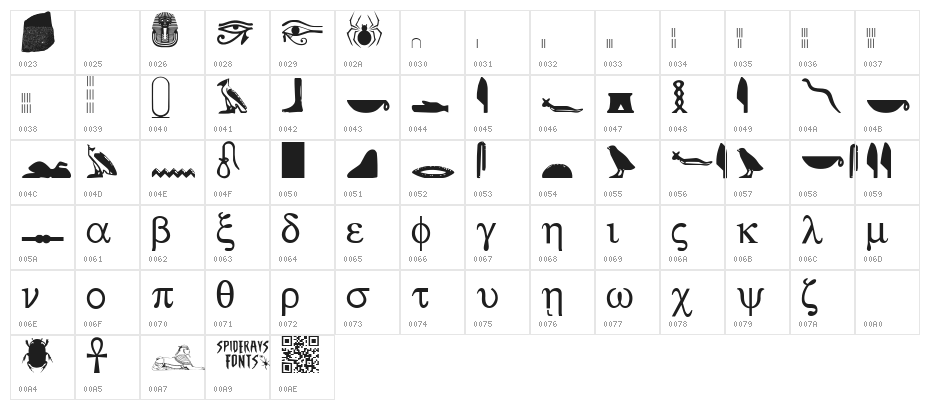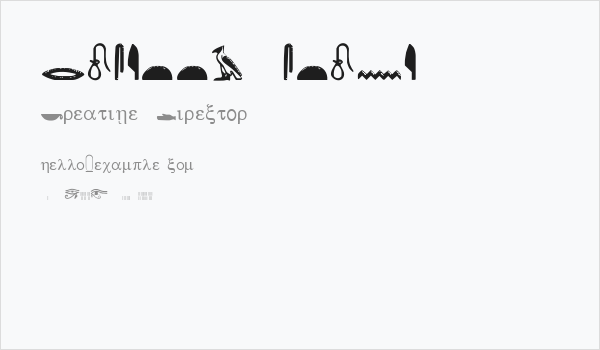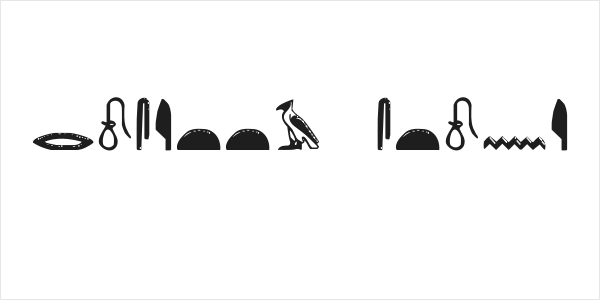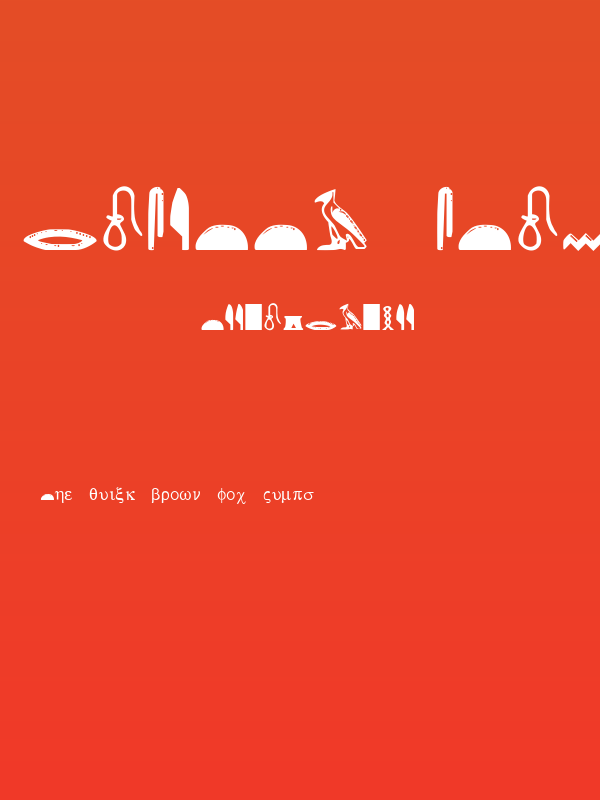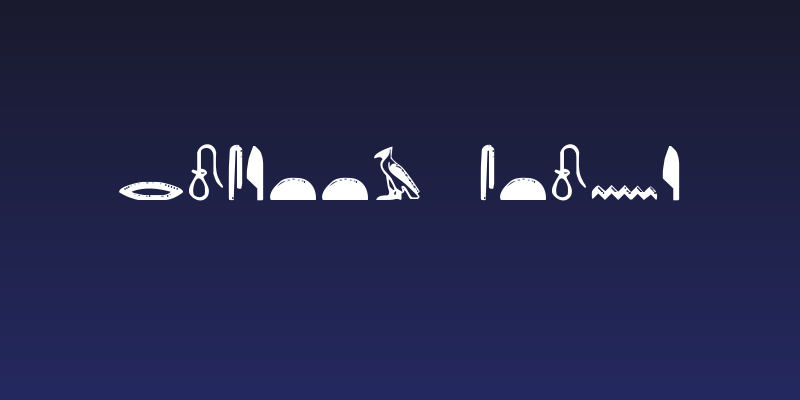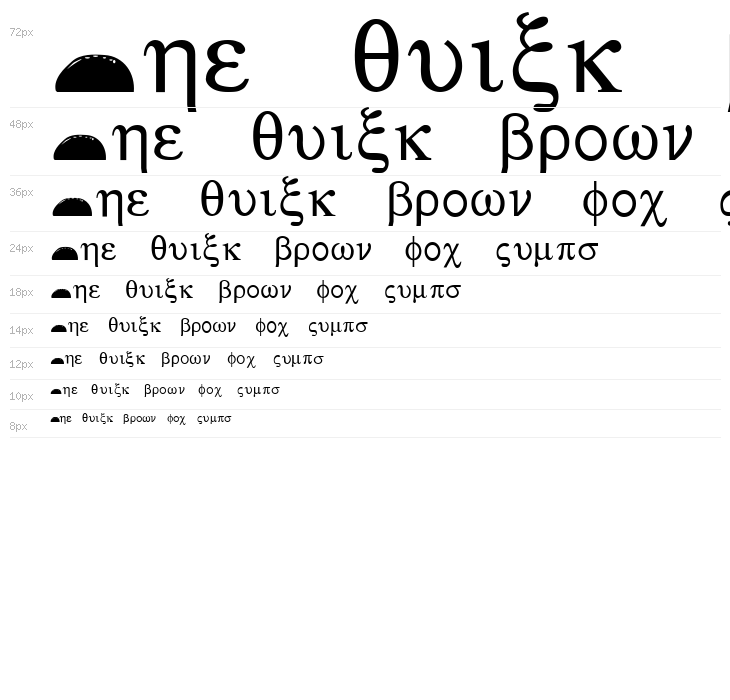
ROSETTA STONE Font
ROSETTA STONE
| Stile generale | Historical, Decorative |
| Caso d'uso | Logos, Educational materials, Themed events |
| Progetti proposti | Ideal for educational materials, historical documentaries, themed events, and cultural exhibitions. |